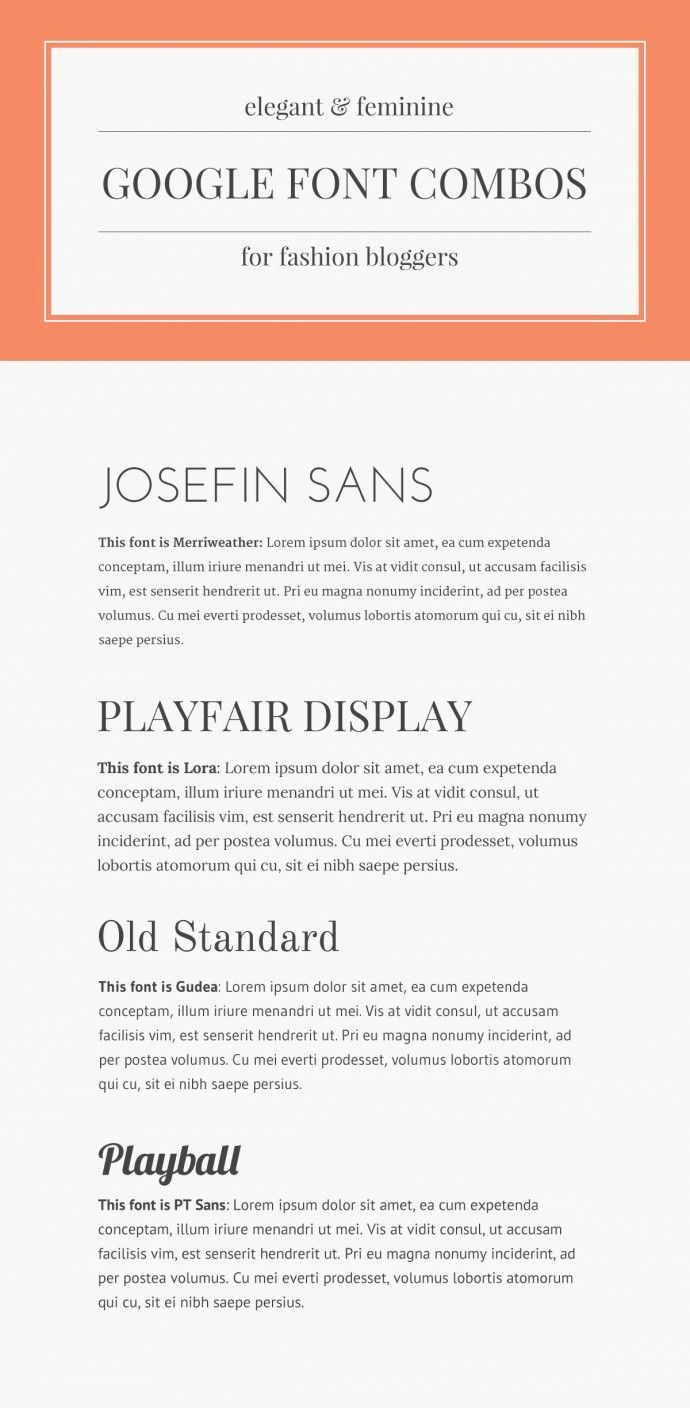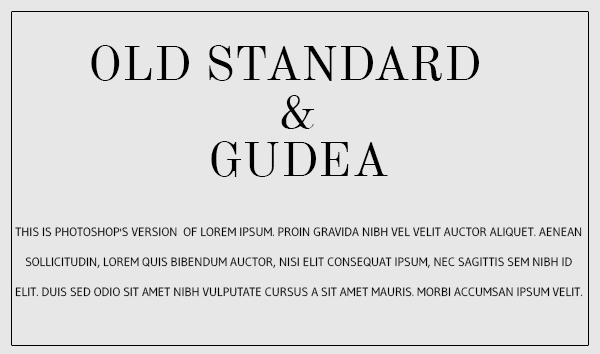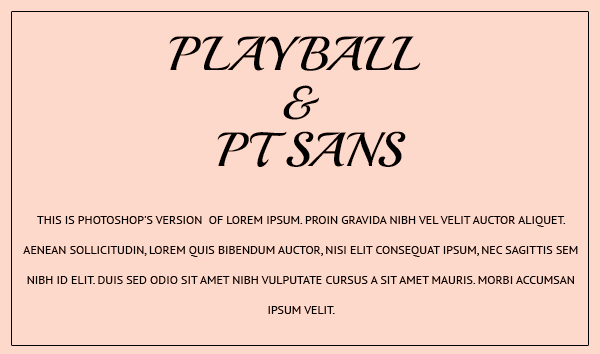
4 combinaisons typographiques élégantes et féminines gratuites pour vos sites web
Voici un exemple de 4 combinaisons élégantes et féminines que vous pouvez utiliser pour votre site internet
Combinaison 1 : Josefin Sans + Merriweather
Josefin Sans + Merriweather
Combinaison 2 : Playfair Display + Lora
Playfair Display + Lora
Combinaison 3 : Old Standard + Gudea
Old-Standard-Gudea
Combinaison 4 : Playball + PT sans
Playball & PT-sans